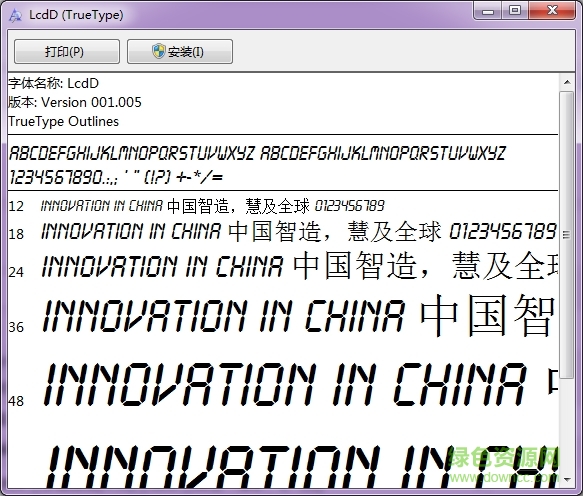
lcdd字體是魔獸世界中使用到的液晶數(shù)字字體,字體微斜,左邊端正右邊圓滑,給你電子表示數(shù)的視覺(jué)呈現(xiàn),如果您對(duì)本字體感興趣,就來(lái)綠色資源網(wǎng)下載收藏吧!
lcd字體是一個(gè)非常優(yōu)質(zhì)的廣告平面設(shè)計(jì)素材,是常見(jiàn)的電子表數(shù)字的字體風(fēng)格,給你的文字更加端正鮮明的視覺(jué)效果,運(yùn)用在數(shù)字提示等內(nèi)容上,絕對(duì)讓你的創(chuàng)意更加突出,傾斜風(fēng)的設(shè)計(jì)讓字體更有自己的獨(dú)特魅力。